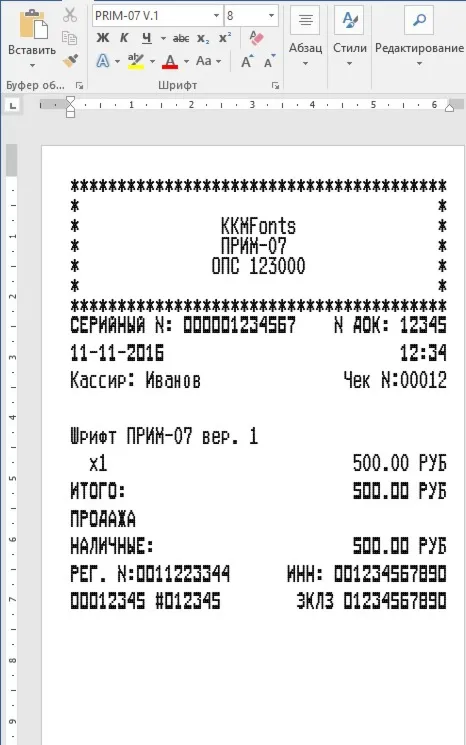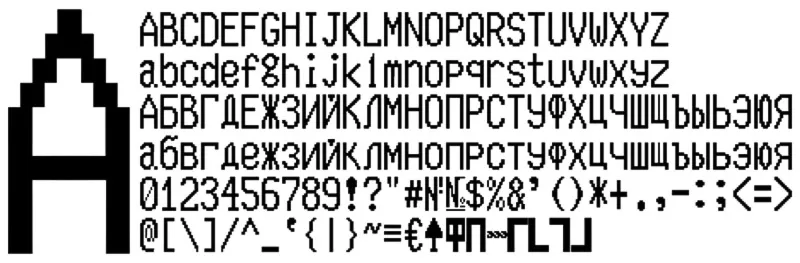
Шрифт кассового аппарата ПРИМ-07 версия 1(матрица 7х9) в формате TTF (русские и английские буквы) для использования в программе Microsoft Word. В архиве находятся стандартный и жирный шрифты в формате TTF и шаблон чека. Вам остается только установить шрифты в систему (обычно C:\WINDOWS\Fonts), открыть шаблон и начать редактирование.